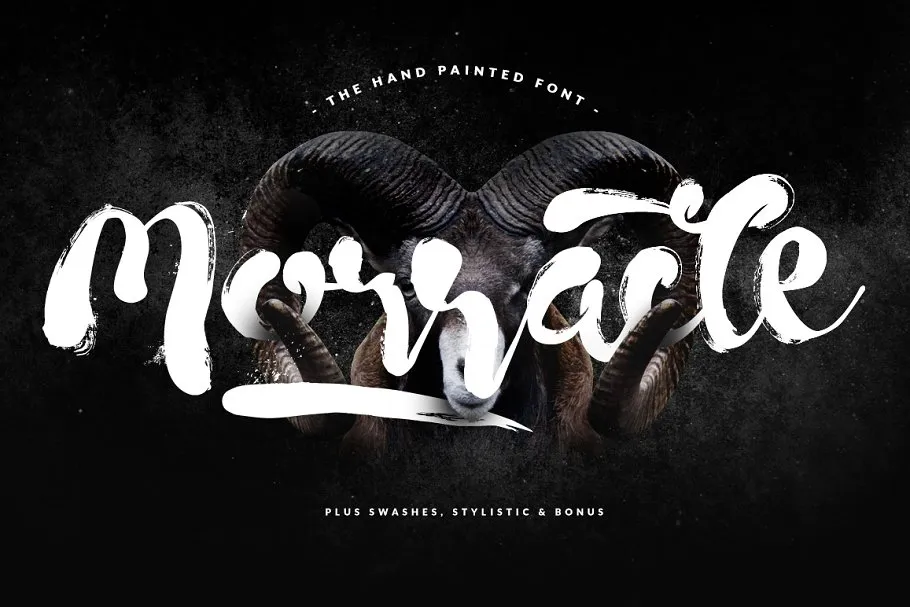
Aqui está uma descrição em português do Brasil para a página de download da fonte ‘Morracle Font’: Descubra agora o Morracle Font, uma fonte brush inspirada nas habilidades artísticas autênticas de traçar com tinta e tons. Inspirado por artistas que transformam suas experiências sensoriais em arte, esta fonte oferece um toque único que complementa perfeitamente qualquer projeto. Selecione o Morracle Font para adicionar uma personalidade única a seus designs digitais. Ele apresenta tons de alternativas gráficas e recursos adicionais, garantindo uma experiência completa e versátil. Com suporte ao vídeo tutorial, este recurso auxilia novatos que estão iniciando neste mundo fascinante. Para usufruir da fonte completo com todas as suas funcionalidades, você terá acesso às fontes em formato TTF (TrueType) e OTF (OpenType), além de suporte a web fonts. Ainda mais, o Morracle Font inclui formas bonus no formato AI (Adobe Illustrator), EPS (Encapsulated PostScript) e PNG, oferecendo inúmeras possibilidades criativas para seus projetos digitais. Descubra agora a arte digital através desta fonte única e convidativa. Instale-a em seu sistema e transforme suas criações digitais em obras de arte com o Morracle Font.